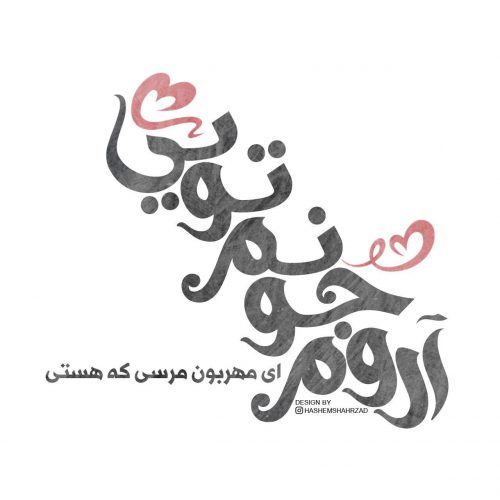
فونت لوگوتایپ عربی آراهالا فونت بسیار زیبا و کاربردی مناسب تایپوگرافی و لوگو می باشد. شما عزیزان می توانید این فونت را در تمامی نرم افزارهای گرافیکی مثل: فتوشاپ، ورد و… و همچنین برای طراحی پوستر، لوگو، لوگوتایپ و… استفاده کنید.فونت عربی آراهالا را آقای ” هاشم شهرزاد ” ویرایش و منتشر کرده اند که دارای حروف گچ پژ نیز می باشد.
Mouhammad Mousa Alkhattat-Dimyat, Dumyat, Egypt
This font support Arabic, and Latin languages in compact and well constructed typographic design
Edit: Hashem Shahrzad